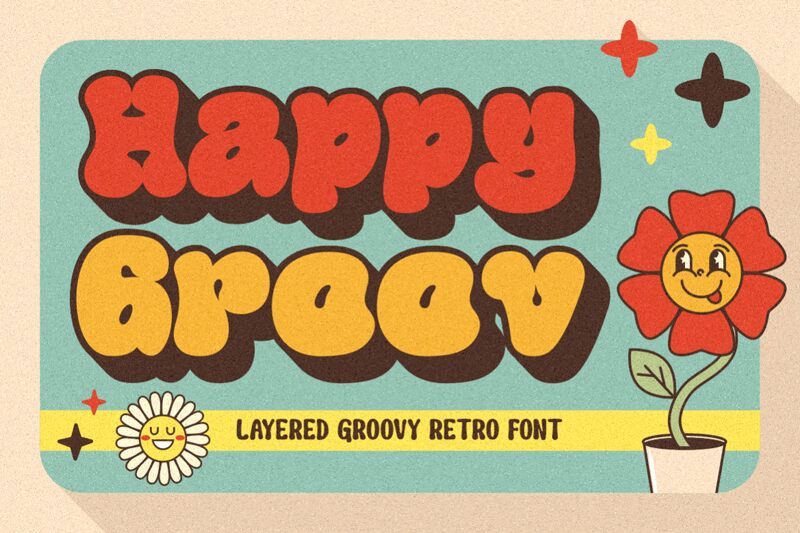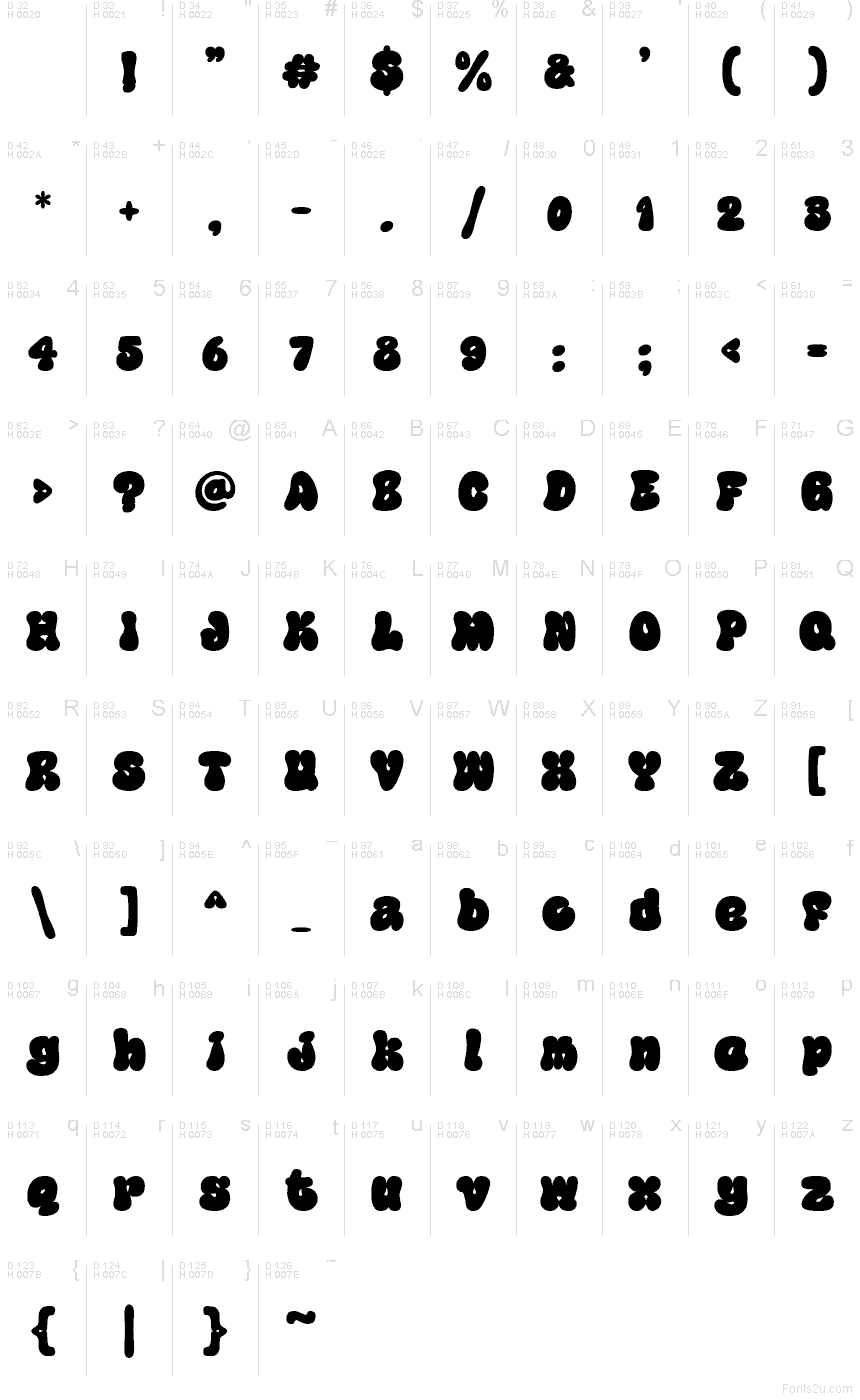
Happy Groov One od Shanaf Studio to darmowy font displayowy w stylu cartoon, pełen radosnej, „groovowej” energii. Litery wyglądają na miękkie i napuchnięte, z mocno zaokrąglonymi cięciami i przysadzistymi proporcjami, co nadaje całemu alfabetowi zabawny, niemal „roztopiony” rytm. Przypomina to bardziej naklejki niż typowe, nudne nawiązania do stylu retro.
Font ten naturalnie sprawdzi się w brandingu produktów dla dzieci, opakowaniach przekąsek, radosnych nagłówkach plakatów, miniaturkach na YouTube, zaproszeniach na imprezy oraz krótkich tekstach, w których darmowy krój ma zapewnić natychmiastowe poczucie ciepła, nie popadając przy tym w przesłodzony klimat. Dzięki pełnym i kompaktowym formom świetnie nadaje się również do plansz tytułowych i napisów w stylu logo, które od pierwszego spojrzenia muszą wyglądać przyjaźnie, zabawnie i wyrazista.